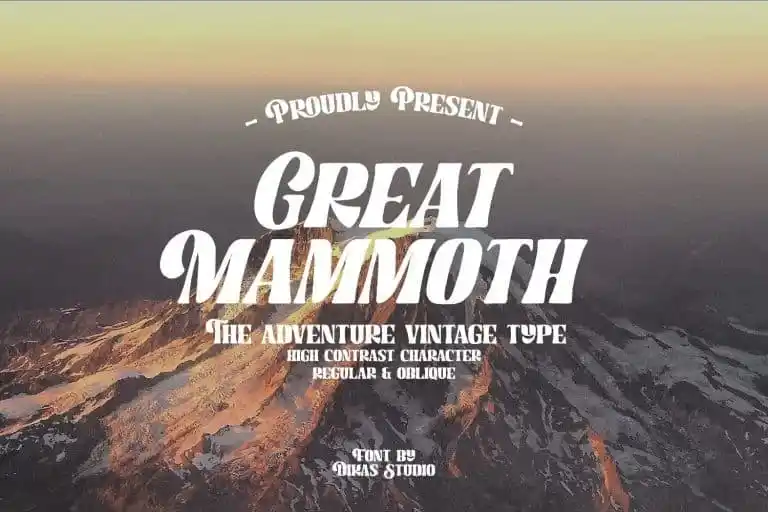
A Great Mammoth Display Font é uma fonte de tipo ilustrado criada pelo designer Andika Setiawan. Essa fonte traz uma sensação clássica e vintage, com traços bruscos e um toque artesanal autêntico. A fonte vem em duas estilos: regular e oblique. Ela se destaca perfeitamente para trabalhos de temática vintage, retro ou aventura, como logotipos, marcações, selos, etiquetas, camisetas e produtos personalizados. Ideal para aqueles que desejam dar um toque único em seus projetos visuais, especialmente aqueles com um estilo mais informal e criativo.